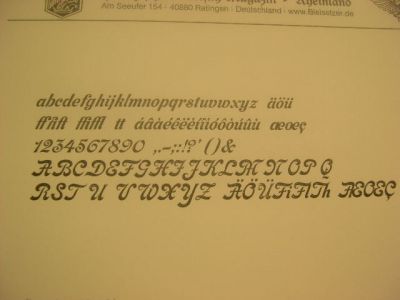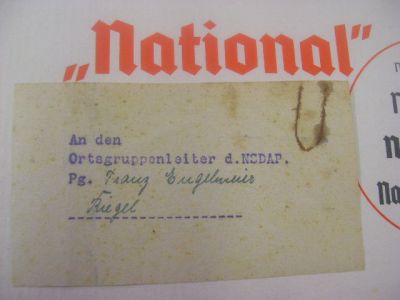
Bitte um professionelle Empfehlung
>Eine Preußische Flagge mit dem Schriftzug "Schriftensammlung" in der
>Mitte. Das mit dem Preußischen gefällt dem Verlag (noch) nicht. Das
>finden sie zu martialisch.
Naja, hier muss ich den Verleger Recht geben. Diese preußische Identität in der Vordergrund wirkt ein bißchen kömisch.
Stammen wirklich alle deine Schriften aus Preußen? Das glaube ich kaum. Aber selbst wenn das so wäre, haben diese Schriften immer noch eine Rolle in unsere Gesellschaft *heute*. Viele davon sind und werden immer noch verwendet, entweder von dir, wenn du für Kunden eventuell druckst, oder von andere Designer, die digitale Versionen den Schriften einsetzen.
Preußen ist ein Land und ein Königreich das nicht mehr gibt. Aber die Schriften bleiben immer noch lebendig. Die Schriften haben ein Leben, dass viel größer als irgendwelche preußische Errinerungen ist.
Wenn du immer noch ein "preußisches" Buch machen willst, kannst du das selbstverständlich machen. Aber du sollst nicht erstaunt werden, wenn Verleger weniger bereit sind, das Buch zu verlegen, und wenn es weniger Käufer findet.
Wieso nicht einfach "gute Schriften", "alte Schriften", "schöne Schriften", "Bleischriften", "meine Bleischriftsammlung" oder sogar "deutsche Schriften" (wenn das wirklich stimmt) als Titel verwenden? Letzendlich geht us doch um so was, oder?
P.S.: Apropos Adler. Ich finde den Adler wirklich wunderschön! Aber viel weniger schön, als alle die Schriftproben, die du bisher gezeigt hast.
Wie Eric Gill ganz gut schrieb: "Letters are things, not pictures of things." Der Adler da, so schön wie er ist, ist kein Ding, sondern nur ein Bild von etwas. Deine Buchstaben aber sind Dinge, die immer noch lebendig sind. Verstehst du, was ich meine? ;-)
Natürlich wirkt es kömisch.
Aber das macht nichts.
Außer Bleisetzer bin ich "nebenher" auch Vertriebsprofi.
Diese Preußen-Sache polarisiert. Und läßt sich so sehr gut vermarkten.
Siehe: Deutscher Drucker vom 27.1.2006:
Siehe: Magazin Publisher, Ausgabe vom 26.3.2006. Dort soll, so sagte man mir jedenfalls, eine Doppelseite über Bleisatz drin sein. Mit Erwähnung und Fotos des Preußischen Bleisatz-Magazin.
Und das ganz bestimmt auch, weil sich jeder (auch die Fach-Redaktionen) sofort fragen "Was soll das?).
Hier kann ich aus eigene Erfahrung sprechen: wenn mann ein Schriftmuster[buch] macht, sollen die Schriften eigentlich in den Vordergrund stehen. Zu Recht sagst du, dass Schrift ein Kulturgut ist. Die Schriften sind Kunstwerke, und unsere Welt ist besser und reicher, weil es sie gibt!
Natürlich wurden nicht alle meine Schriften in Preußen gegossen.
Das habe ich auch nie behauptet.
Aber mein Bleisatz-Magazin liegt in Preußen.
Würde es Düsseldorfer Bleisatz-Magazin heißen, wären auch nicht alle Schriften aus Düsseldorf.
Preußen ist eine Einstellung und eine innere Haltung.
Preußen ist eine Herkunft. Meine Herkunft.
Und auch die Herkunft der Schriften-Entwerfer, die in der Zeit von 1900 bis 1940 die (aus meiner Sicht) schönsten Bleisatz-Schriften entworfen haben.
Meine Leidenschaft gehört dem Bleisatz und der deutschen Geschichte. Jedesmal, wenn ich eine alte Bleisetzerei auflöse, die teilweise seit 1960 im Dornröschen-Schlaf war und seit Generationen in Familienbesitz war, finde ich Gegenstände aus der Preußen-Zeit - Klischees, handschriftliche Notizen, alles mögliche. Ich habe mittlerweile einen "Giftschrank" - eine Stehsatz-Schublade, in die ich alles reinlege, was ich aus dem Verkehr ziehen will:
Kennst Du die Tannenberg von Stempel?
Weißt Du, was Tannenberg bedeutete?
Die National:
Kennst Du den "Führer-Erlaß" von 1941, der die amtliche Verwendung von Fraktur-Schriften verbietet?
Weißt Du, daß Lucian Bernhard Jude war und Deutschland gerade noch verlassen konnte?
Ich sehe die Bleisatz-Schriften immer auch im Kontext mit ihrer jeweiligen Epoche. Beides war in Interaktion miteinander.
Vermutlich siehst Du diese Bleisatz-Schriften völlig unpolitisch?
Damit habe ich kein Problem. Ich sehe das anders.
Verstehe mich richtig:
Die Beschäftigung mit dem Bleisatz ist ein Luxus, den ich mir leiste.
Eine für mich ganz untypische Situation. Ich lebe nicht davon. Ich produziere nichts. Ich habe keinen Zeitdruck außer dem, den ich mir selbst auferlege. Das ist herrlich. Und ein absolut notwendiger Gegenpol zu meinem Tagesjob als Vertriebsleiter einer Telefongesellschaft. In meinem Job geht es immer "Entscheidung sofort. Jetzt." Und es geht immer um sehr viel. Habe ich davon genug, gehe ich in meine Setzerei. Da "können sie mich alle mal."
Und ich baue ab und an Collagen aus Bleisatz und Holzlettern.
Das hier ist Ça ira.
Daran habe ich drei Monate gebaut. Ich mußte mich dazu in diverse Literatur einlesen (November-Revolution 1918). Damals habe ich für mich neu definiert, was ich unter "Gott" verstehe. Alles das ist in Ça ira drin.
Vermutlich war die Einstellung der Schriftenschöpfer und -gießer die gleiche wie in der Gesamtbevölkerung: Es gab viele Mitläufer und nur sehr wenige, die Widerstand geleistet haben. Daraus kann zumindest ich niemandem einen Vorwurf machen. Weiß ich ja nicht, ob ich selbst den Mut gehabt hätte, z.B. als nationaler Rechter in enger Zusammenarbeit mit Gewerkschaftsfunktionären eine Widerstandsgruppe zu bilden. Ich bezweifle das eher.